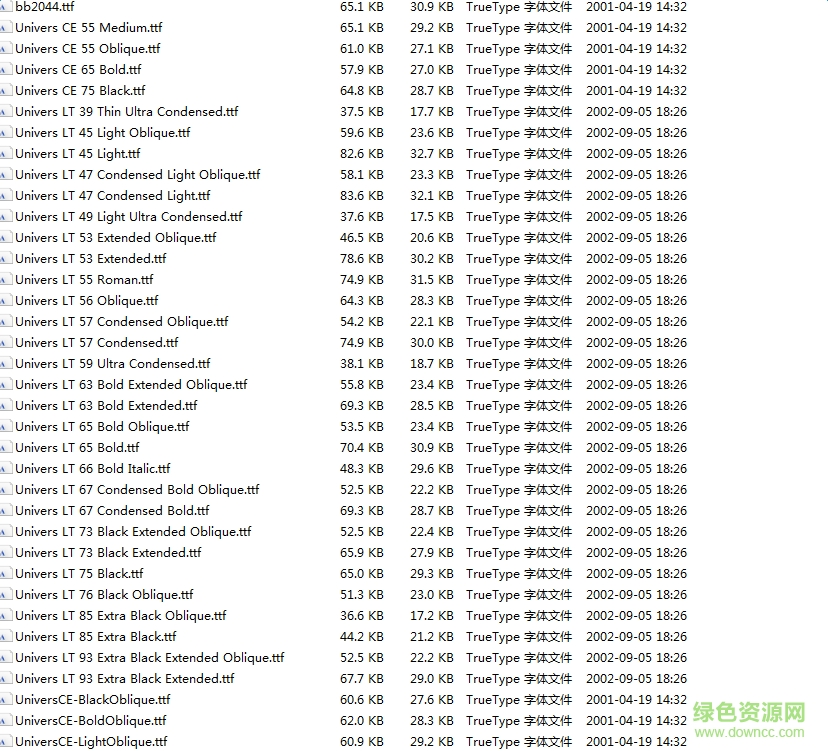
univers系列字體
univers字體是一種優(yōu)雅精致的無襯線英文字體,細(xì)節(jié)的表現(xiàn)力非常出色,小編為大家搜集整理了幾十款最常用univers系列字體,喜歡這款字體的朋友歡迎在綠色資源網(wǎng)下載!
Univers字體介紹
Univers字體是一種西文無襯線字體。在平面設(shè)計(jì)界,它和helvetica一起被稱為瑞士風(fēng)格字體,最初是作為法國Deberny,Peignot鉛字鑄造所的照相排版鉛字發(fā)表的。